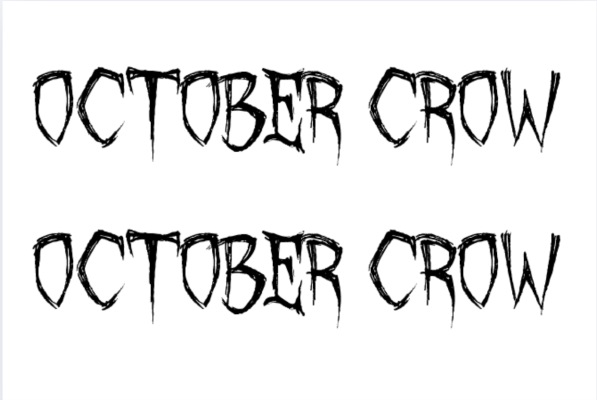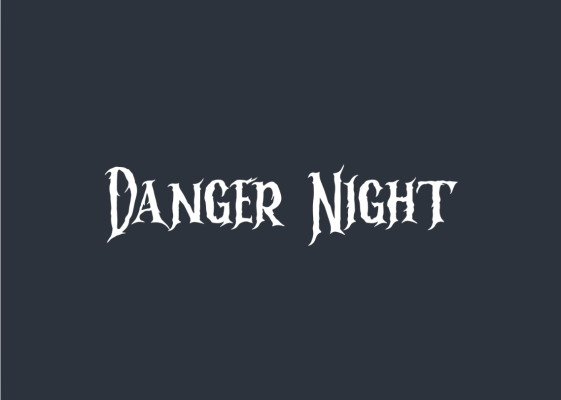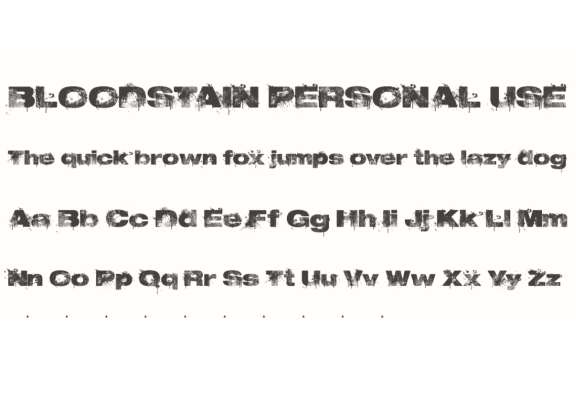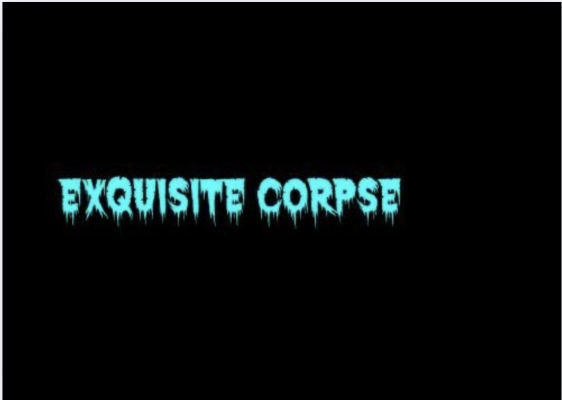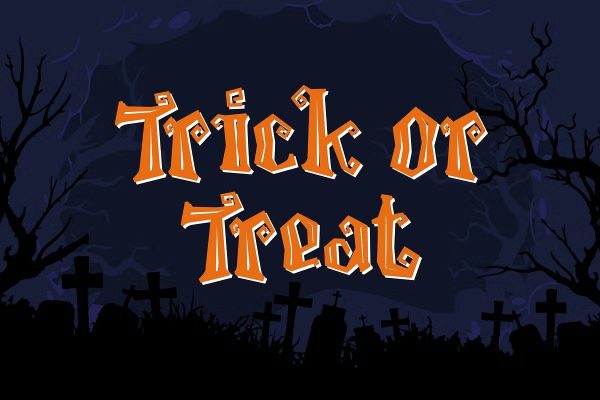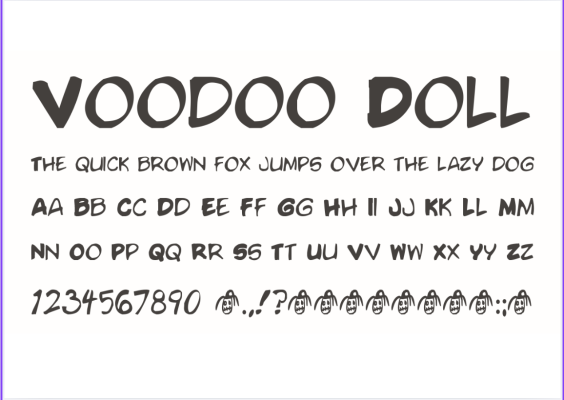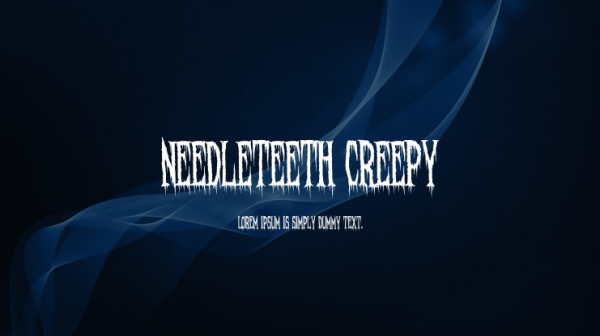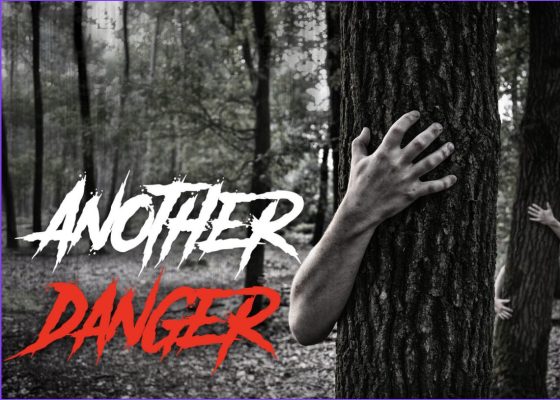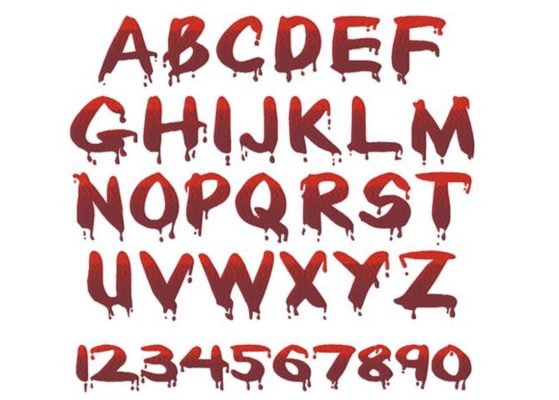
[Tuyển tập] 10+ Font chữ Halloween kinh dị nhất cho banner, poster
Halloween đang đến gần – mùa lễ hội của những ánh đèn ma mị, tiếng cười rợn người và phong cách thiết kế “rùng rợn” khó quên. Để tạo nên không khí kinh dị đúng chuẩn, bạn không thể bỏ qua yếu tố font chữ – chi tiết nhỏ nhưng quyết định vibe của toàn bộ ấn phẩm. Cùng khám phá tuyển tập 10+ font chữ Halloween kinh dị nhất, giúp thiết kế của bạn “hù” người xem ngay từ cái nhìn đầu tiên!
Đặc điểm nhận diện chữ Halloween kinh dị
Chữ Halloween vibe kinh dị không chỉ đơn thuần là một kiểu chữ. Nó là “ngôn ngữ thị giác” kể nên câu chuyện của mùa lễ hội: rùng rợn, ma mị nhưng vẫn cuốn hút và đầy sáng tạo.
Những đặc trưng thường thấy của dạng chữ này gồm:
• Nét chữ sắc, méo hoặc nhỏ giọt như máu, xương, hoặc bóng tối lan tỏa.
• Tông màu chủ đạo: cam, đen, đỏ, tím – biểu tượng của sự bí ẩn và rợn người.
• Hiệu ứng đặc trưng: rạn nứt, đổ bóng, lóa sáng hoặc trồi lên như từ “nghĩa địa”.
• Cảm giác truyền tải: có thể là ma mị, rùng rợn hoặc “đáng sợ vui nhộn” – rất hợp với các chiến dịch Halloween hướng đến giới trẻ hoặc sự kiện cộng đồng.
Nhờ vậy, chữ Halloween vibe kinh dị thường được ứng dụng trong:
• Poster sự kiện và banner quảng cáo,
• Mở đầu video, intro hoặc content TikTok,
• Thiệp mời, áo in, sticker và bao bì sản phẩm theo mùa.
Đây chính là yếu tố giúp thiết kế trở nên ấn tượng, gợi cảm xúc ngay tức thì – điều mà các marketer, designer đều hiểu rõ khi chọn font chữ Halloween phù hợp cho dự án của mình.
Top 10+ Font chữ Halloween kinh dị nhất năm 2025
Cùng điểm qua những font chữ Halloween vibe kinh dị “gây sốt” nhất năm 2025, đang được cộng đồng sáng tạo sử dụng rộng rãi trong các thiết kế lễ hội.
October Crow
Font chữ mang vẻ u ám cổ điển, gợi hình ảnh bầu trời đêm tháng Mười cùng tiếng quạ kêu vang giữa rừng sương mờ — hoàn hảo cho poster và tiêu đề lễ hội.
Font chữ October Crow
Exquisite Corpse
Những nét chữ méo mó, như được ghép từ linh hồn lang thang, tạo cảm giác ghê rợn và bí ẩn, cực kỳ hợp cho bìa truyện hay banner Halloween.
Font chữ Exquisite Corpse
Monster Pumpkin
Tròn trịa, phá cách và ngộ nghĩnh, font này mang tinh thần Halloween và vẫn “rợn nhẹ”, rất hợp với thiết kế hướng đến GenZ.